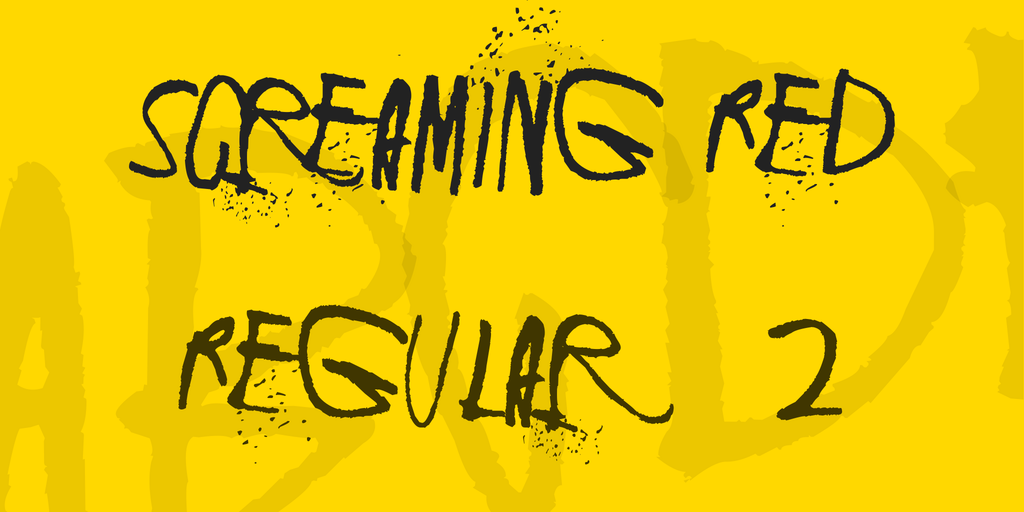
Screaming Red Font Family
Estamos muito felizes por você ter baixado a nossa fonte ‘Screaming Red Font Family’. Esta elegante fonte brush é perfeita para criar uma vibe vibrante e animada em projetos pessoais, seja para criar cartões de aniversário, desenhos faciais ou até mesmo para adicionar um toque especial ao seu portfolio. Para os profissionais que buscam dar vida à sua identidade visual, a fonte oferece grande flexibilidade – além da versão gratuita personalizada, também temos uma licença comercial disponível. Para usuários comerciais, precisamos de uma pequena contribuição: 15€ ou $20, enviada através do PayPal. Em seguida, é só enviar-nos um email para confirmar o seu pagamento e solicitar as instruções para instalar a fonte. Para quem deseja dar sua contribuição sem esperar por uma grande recompensa, temos também a opção de fazer uma doação regular através do botão à esquerda da página de download. Não se preocupe, esta doação é totalmente voluntária e serve para apoiar a nossa missão de manter gratuitas as melhores fontes brush disponíveis no mercado. Junte-se a nós neste projeto gratificante de democratizar o acesso a uma rica gama de recursos gráficos, incluindo cores vibrantes e estilos atemporais. Com ‘Screaming Red Font Family’, transforme seu design em algo único e poderoso.